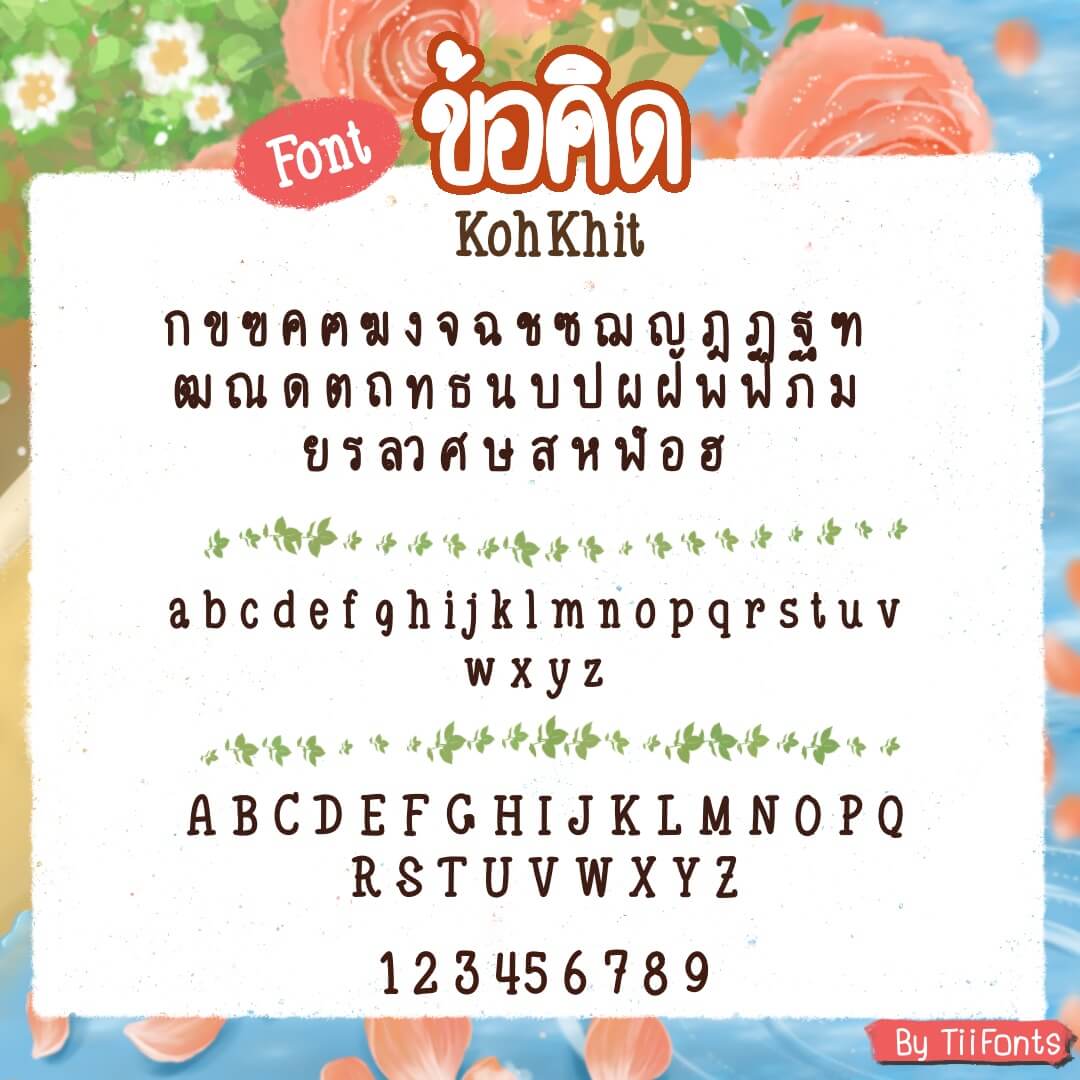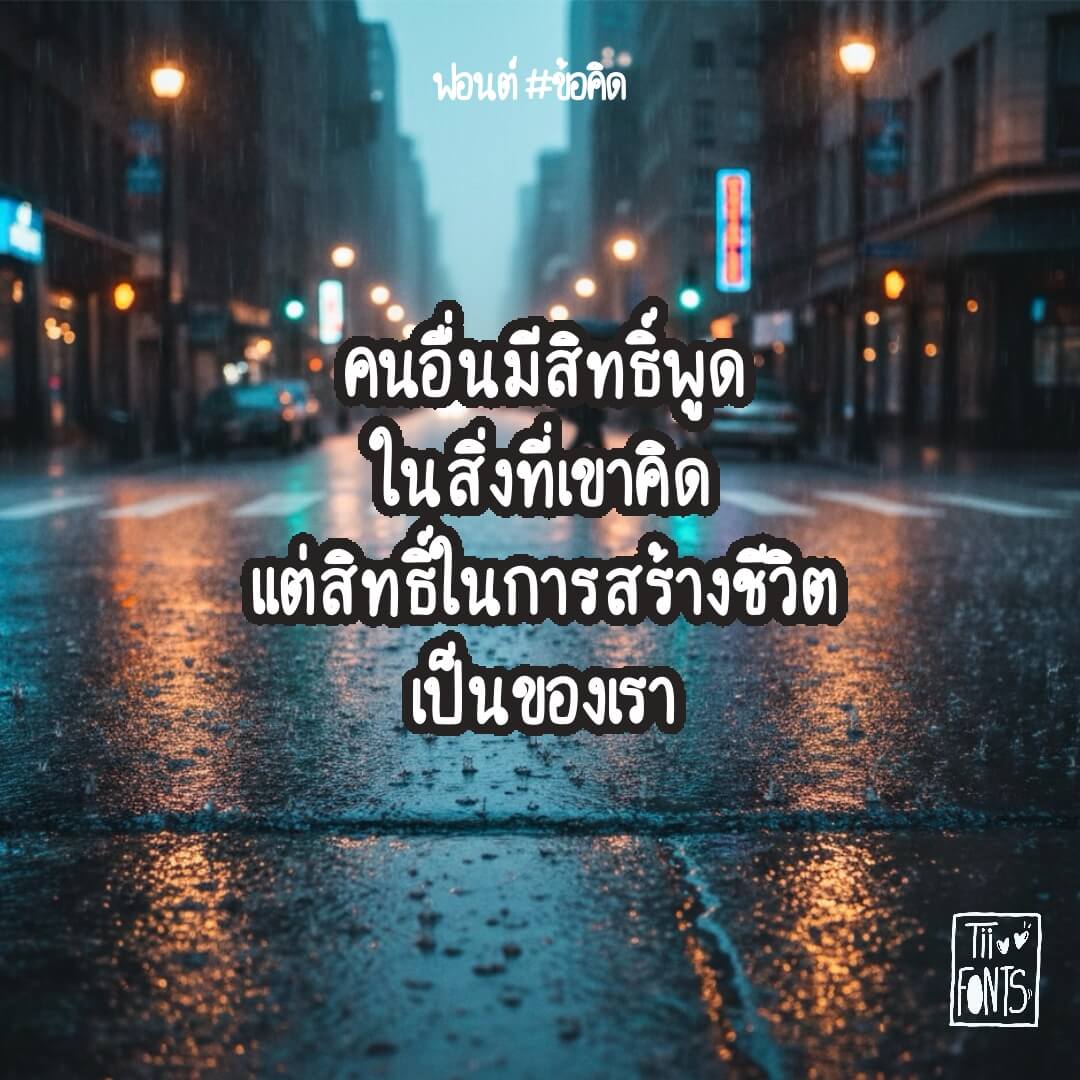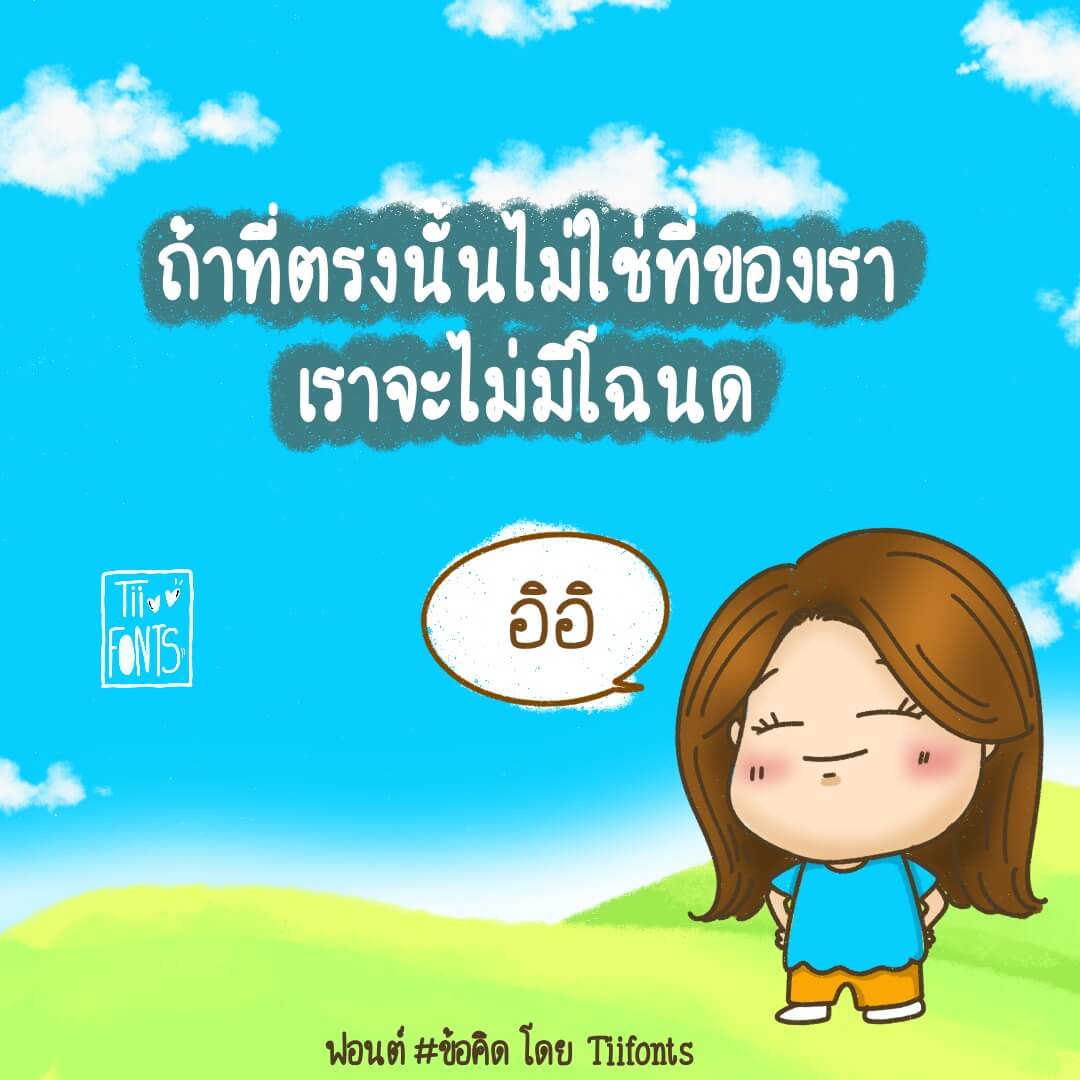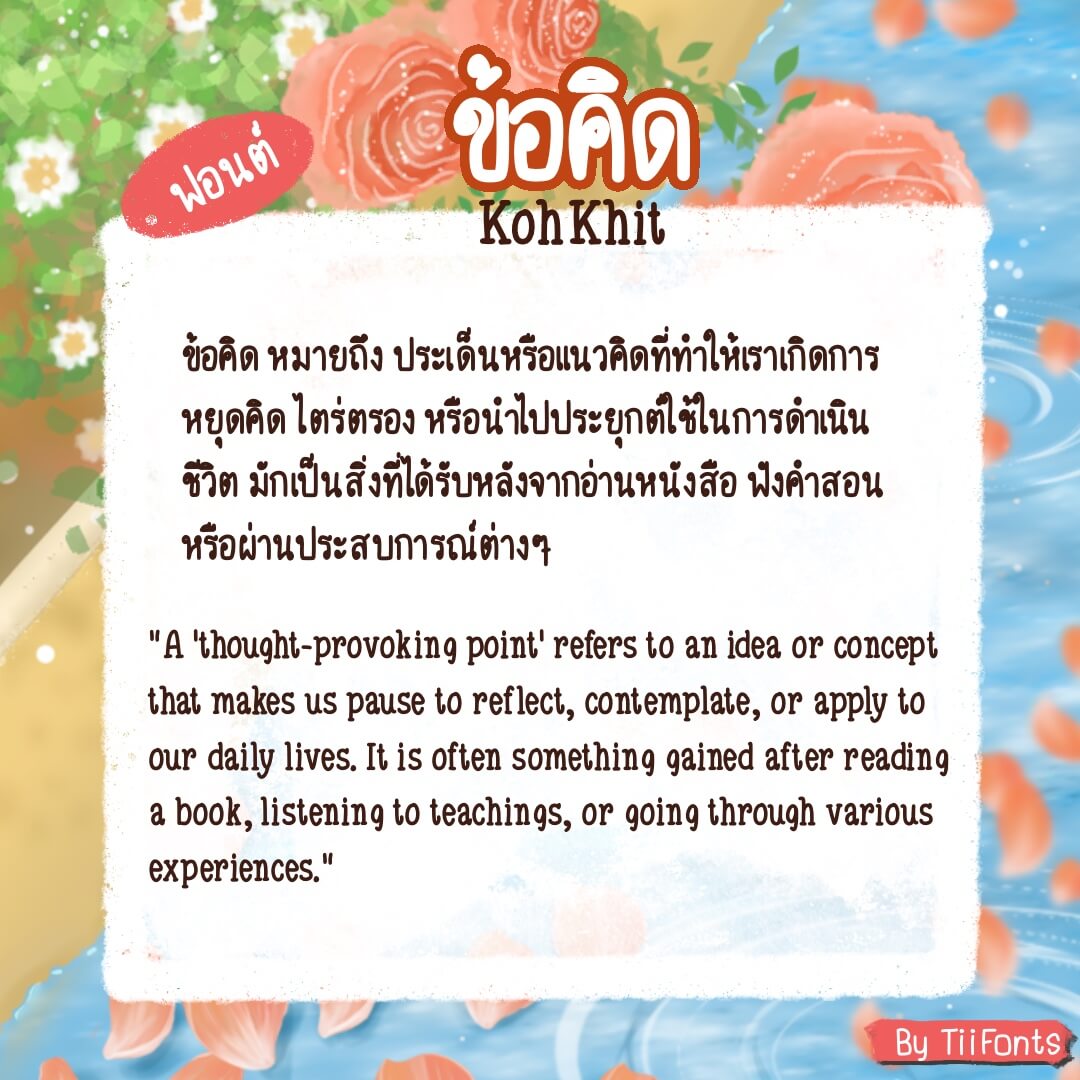
ให้ทุกข้อความของคุณละมุนขึ้น ด้วยฟอนต์สไตล์เรียบง่ายแต่แฝงความรู้สึก เป็นกันเอง อ่านง่ายสบายตา
ทำไมต้องมีฟอนต์ “ข้อคิด”?
✅ อ่านง่าย: ตัวอักษรชัดเจน ไม่ซับซ้อน
✅ มีเอกลักษณ์: ให้ความรู้สึกเหมือนเขียนด้วยลายมือแบบตั้งใจ
✅ ดีต่อใจ: ใช้เขียนเรื่องราวดีๆ หรือประโยคที่ช่วยฮีลใจได้ดีสุดๆ
”เพราะทุกความคิด… มีคุณค่าเสมอ” ให้ฟอนต์ข้อคิดช่วยส่งต่อความคิดดีๆ ของคุณนะคะ